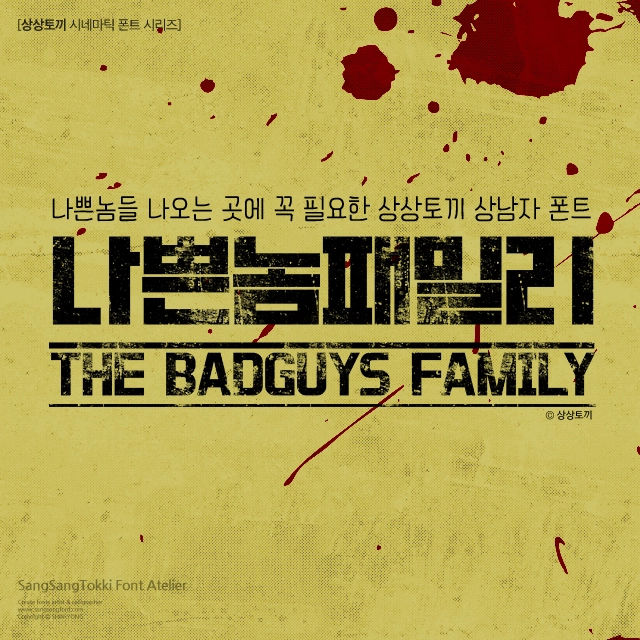
나쁜놈 패밀리 5종
나쁜놈들 나오는 곳에 꼭 필요한 상상토끼 상남자 폰트, 나쁜놈 패밀리 5종
한글 2,856자 / 영문 52자 / 약물 54자
나쁜놈 Regular 1종
나쁜놈 Hardboiled 1종
나쁜놈 Military 1종
나쁜놈 Noir 1종
나쁜놈 Don-Zorba 1종